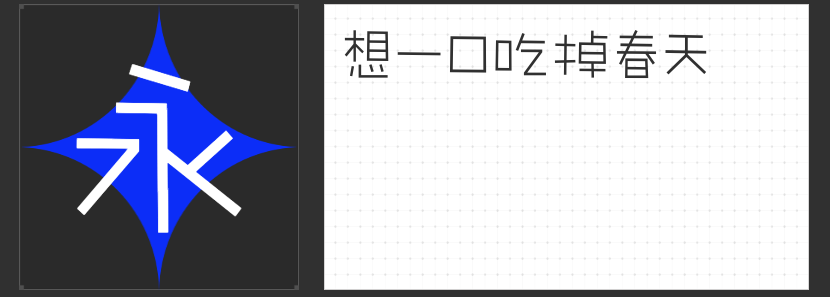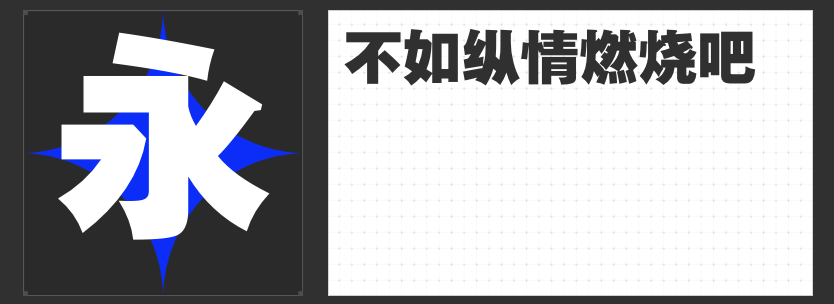
四款综艺设计创意字体推荐:解锁视觉灵感的创意密码
在综艺节目的视觉设计中,字体不仅是信息传递的载体,更是营造氛围、强化主题的关键元素。一款兼具个性与表现力的创意字体,能让画面瞬间抓住观众眼球,为节目注入鲜活的生命力。以下四款风格迥异的创意字体,以独特的设计语言满足综艺设计的多元需求,助力设计师打造令人过目难忘的视觉盛宴。
一、励字敲可爱简 细体
这款字体以手写质感为核心,通过圆润流畅的线条传递出无拘无束的童真趣味。其笔画在保留辨识度的基础上进行适度简化,省略非关键转折,以简洁明快的直线组合勾勒出活泼形态。字型大小微妙变化与错落布局,营造出自然书写的随性美感,仿佛设计师信手拈来的即兴创作。这种不刻意的“不完美”,恰与综艺轻松诙谐的调性完美契合,尤其适合青春类、亲子类节目的标题设计或互动环节的视觉呈现。
二、字恋狂漫野 摇风
以手写感为基底,这款字体通过张弛有度的结构与通透的布白空间,构建出富有韵律的视觉节奏。钩笔画与弯钩的“去钩处理”打破传统字体的规整感,而“笔画断开”的细节设计则赋予字体呼吸感。字型大小错落有致,如同音符在五线谱上跳跃,使静态文字产生动态叙事力。其简洁而不失变化的线条,既能驾驭竞技类节目的紧张氛围,也能为脱口秀等语言类节目增添灵动气质。
三、小豆岛默陌写意水墨简
这款字体将传统书法的写意精神与现代设计语言巧妙融合,笔锋流转间尽显洒脱气韵。锋芒毕露的笔尾与灵动点缀的笔触,既保留水墨的韵律感,又通过适度夸张的变形强化视觉冲击力。其清雅含蓄的格调,既能胜任文化类综艺的标题设计,传递诗意与哲思;也能以反差感为娱乐类节目注入艺术气息,打破常规视觉框架。
四、励字励黑简
作为一款超粗壮的无衬线字体,励字励黑简以方正字形与均匀笔划构建出稳重醒目的视觉基底。方头起笔与无字肩折笔的设计,赋予字体强烈的现代工业感,而超粗笔划则确保其在复杂背景中依然清晰可辨。这款字体尤其适合综艺中的重点信息呈现,如嘉宾姓名、比分公示或悬念标题,以不可忽视的存在感强化观众记忆点。
从俏皮灵动到力量稳重,从传统韵味到现代节奏,这四款字体以差异化设计语言覆盖综艺设计的核心场景。设计师可根据节目调性自由组合搭配,让文字成为传递情绪、塑造风格的第一视觉符号。